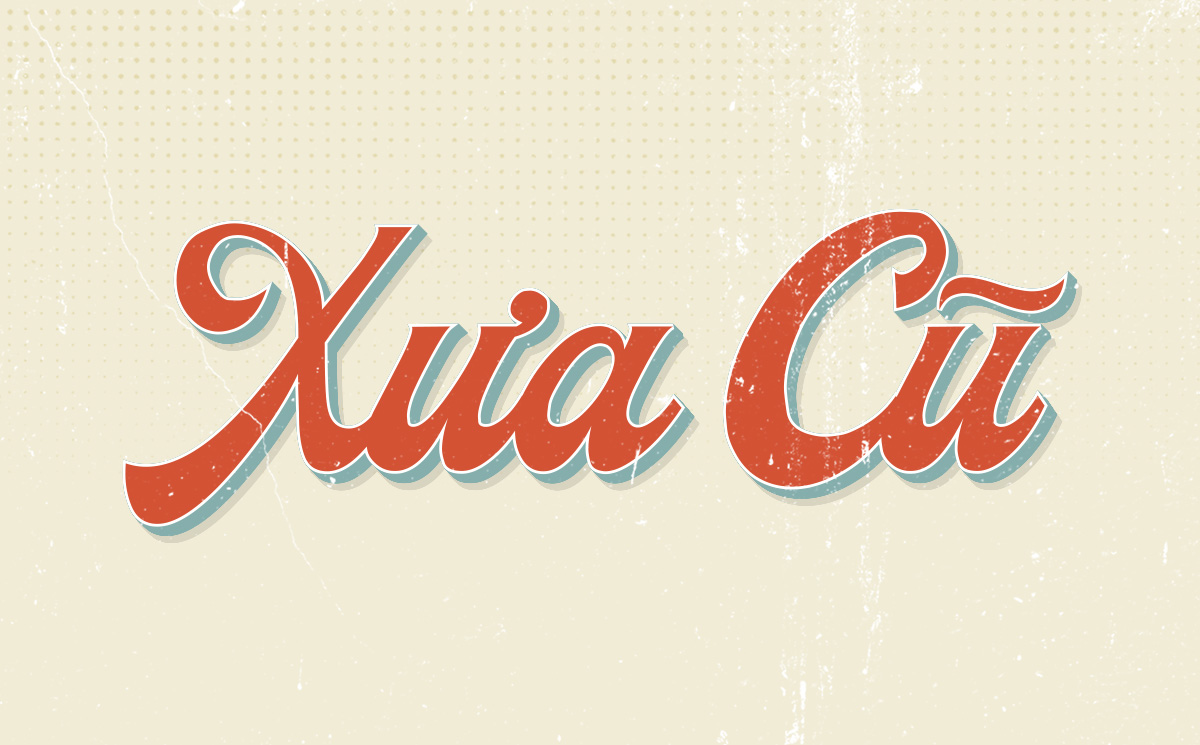
Nhiều designer khi làm poster retro, bảng hiệu quán cà phê hoặc bộ nhận diện mang hơi hướng hoài cổ thường mất khá nhiều thời gian để tìm đúng kiểu chữ. Không ít font nhìn “có vẻ vintage” nhưng khi gõ tiếng Việt lại lỗi dấu, thiếu ký tự hoặc không giữ được tinh thần Sài Gòn xưa như mong muốn. Ở bài viết này, Xưởng In Viva sẽ tổng hợp các bộ font chữ sài gòn xưa việt hóa free phù hợp để bạn dễ ứng dụng vào thiết kế và in ấn nhé.
Một số font chữ Sài Gòn xưa phổ biến
Hiện nay có khá nhiều font được thiết kế hoặc Việt hóa theo phong cách Sài Gòn xưa. Tuy nhiên, không phải font nào cũng giữ được cảm giác hoài cổ đúng tinh thần, đặc biệt khi dùng cho tiêu đề lớn, logo hoặc bảng hiệu.
Vì vậy, trước khi tải font chữ sài gòn xưa, bạn nên xem trước phong cách nét chữ để chọn đúng chất retro mà dự án đang cần. Một số font thường được nhắc đến khi tìm font chữ sài gòn xưa free:
| Font | Phong cách | Ứng dụng | Hỗ trợ tiếng Việt |
|---|---|---|---|
| Saigon Display | Retro | Poster | Có |
| Vintage Saigon | Retro | Logo | Có |
| Saigon Script | Biển hiệu | Có |
| Old Saigon | Retro | Branding | Có |
Khi tìm font chữ sài gòn xưa việt hóa free, bạn nên ưu tiên các phiên bản đã hỗ trợ đầy đủ tiếng Việt. Điều này đặc biệt quan trọng nếu thiết kế của bạn có tiêu đề, slogan hoặc nội dung mang tính nhận diện thương hiệu bằng tiếng Việt.
05 đặc điểm nổi bật của font chữ Sài Gòn xưa
Điều khiến font phong cách Sài Gòn xưa trở nên hấp dẫn không nằm ở việc nó “cũ”, mà ở chỗ nó tạo ra bầu không khí rất khác so với các font hiện đại. Chỉ cần thay đúng kiểu chữ, thiết kế có thể chuyển ngay từ cảm giác trung tính sang hoài cổ và gợi nhớ ký ức thị giác của một thời kỳ cụ thể.
Dưới đây là những đặc điểm nổi bật thường thấy ở nhóm font chữ sài gòn xưa việt hóa:
- Nét chữ đậm và có cá tính: nhiều font mô phỏng chữ bảng hiệu nên tạo cảm giác mạnh, dễ thu hút ánh nhìn.
- Phong cách retro rõ rệt: chỉ cần nhìn vào hình dáng chữ là đã gợi liên tưởng đến poster, bảng hiệu hay biển tiệm xưa.
- Đường nét độc đáo: không đều và “phẳng” như nhiều sans-serif hiện đại, mà thường có độ nhấn thị giác riêng.
- Phù hợp với tiêu đề lớn: rất hiệu quả khi dùng cho poster, logo, tên quán hoặc slogan ngắn.
- Dễ kết hợp với bảng màu retro: đặc biệt hợp với các gam vàng, đỏ, xanh lá cũ, xanh dương cổ điển hoặc nâu vintage.
Nhờ những đặc điểm này, font chữ sài gòn xưa việt hóa free không chỉ đơn thuần là công cụ hiển thị chữ, mà còn là một phần tạo nên bối cảnh và tinh thần cho thiết kế.
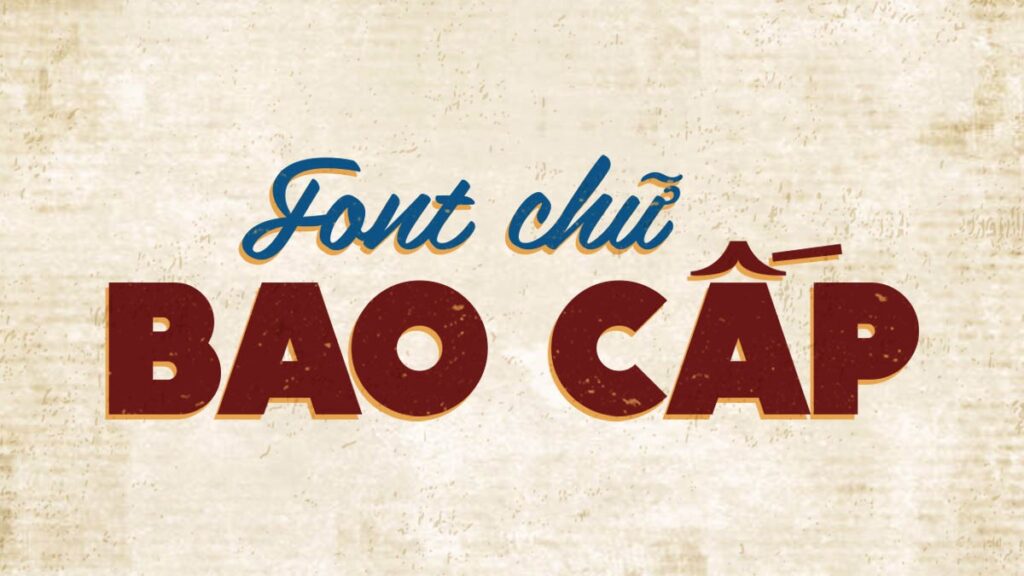
Ứng dụng của font chữ Sài Gòn xưa trong thiết kế
Font kiểu Sài Gòn xưa không dành cho mọi kiểu bố cục, nhưng khi đặt đúng bối cảnh, nó có thể tạo ra hiệu quả thị giác rất mạnh. Đây là nhóm font phù hợp với những dự án cần cảm giác bản địa, hoài niệm và có chất riêng rõ ràng.
Một số ứng dụng phổ biến khi sử dụng font sài gòn xưa việt hóa gồm:
- Poster retro hoặc poster quảng cáo phong cách cũ.
- Logo quán cà phê, tiệm ăn, tiệm bánh hoặc thương hiệu mang hơi hướng hoài niệm.
- Thiết kế bảng hiệu hoặc menu phong cách vintage.
- Branding cho các dự án lấy cảm hứng từ Sài Gòn xưa.
- Thiết kế áo thun, postcard, bao bì hoặc nhãn dán retro.
- Ấn phẩm truyền thông cho sự kiện theo concept xưa cũ.
Nhờ chất riêng trong đường nét, font chữ sài gòn xưa việt hóa free giúp thiết kế không chỉ đẹp hơn mà còn dễ gợi cảm xúc, đặc biệt với những dự án cần tạo dấu ấn văn hóa hoặc phong vị địa phương.
Các lỗi thường gặp khi tải font chữ Sài Gòn xưa
Dù các font retro nhìn rất cuốn hút, nhưng không phải bộ nào tải về cũng dùng được ngay. Nhiều người gặp lỗi khi cài đặt hoặc khi gõ tiếng Việt, đặc biệt là với các font chỉ mô phỏng hình thức vintage nhưng chưa hoàn thiện phần ký tự.
Một số lỗi phổ biến khi tải font chữ sài gòn xưa gồm:
- Font chưa việt hóa: nhìn đẹp nhưng bị lỗi dấu hoặc thiếu ký tự khi gõ tiếng Việt.
- Thiếu bảng chữ: không có đủ chữ hoa, chữ thường, số hoặc các ký tự đặc biệt cần thiết cho thiết kế.
- Font không tương thích phần mềm: một số font hoạt động không ổn định trong Illustrator hoặc Photoshop.
- File font bị lỗi: tải từ nguồn không ổn định nên không thể cài đặt hoặc dùng không đầy đủ.
Để hạn chế những lỗi này, bạn nên chọn bộ font chữ sài gòn xưa việt hóa free từ nguồn đáng tin cậy và thử gõ tiếng Việt trước khi đưa vào dự án chính thức.
Một số lưu ý khi sử dụng font chữ Sài Gòn xưa
Font retro rất dễ tạo ấn tượng, nhưng nếu dùng không đúng cách thì thiết kế cũng rất dễ trở nên rối mắt hoặc bị “quá tay”. Đây là loại font có cá tính mạnh, vì vậy cần dùng đúng vị trí để phát huy hiệu quả.
Khi sử dụng font chữ sài gòn xưa việt hóa free, bạn nên lưu ý:
- Không dùng cho đoạn văn dài: font retro phù hợp nhất với tiêu đề, slogan hoặc những cụm chữ ngắn có tính nhấn mạnh.
- Kết hợp với font hiện đại hoặc trung tính: cách này giúp bố cục dễ đọc hơn và giữ được sự cân bằng thị giác.
- Chọn màu sắc phù hợp: nếu muốn giữ đúng tinh thần vintage, nên đi cùng bảng màu retro thay vì những màu quá hiện đại hoặc quá lạnh.